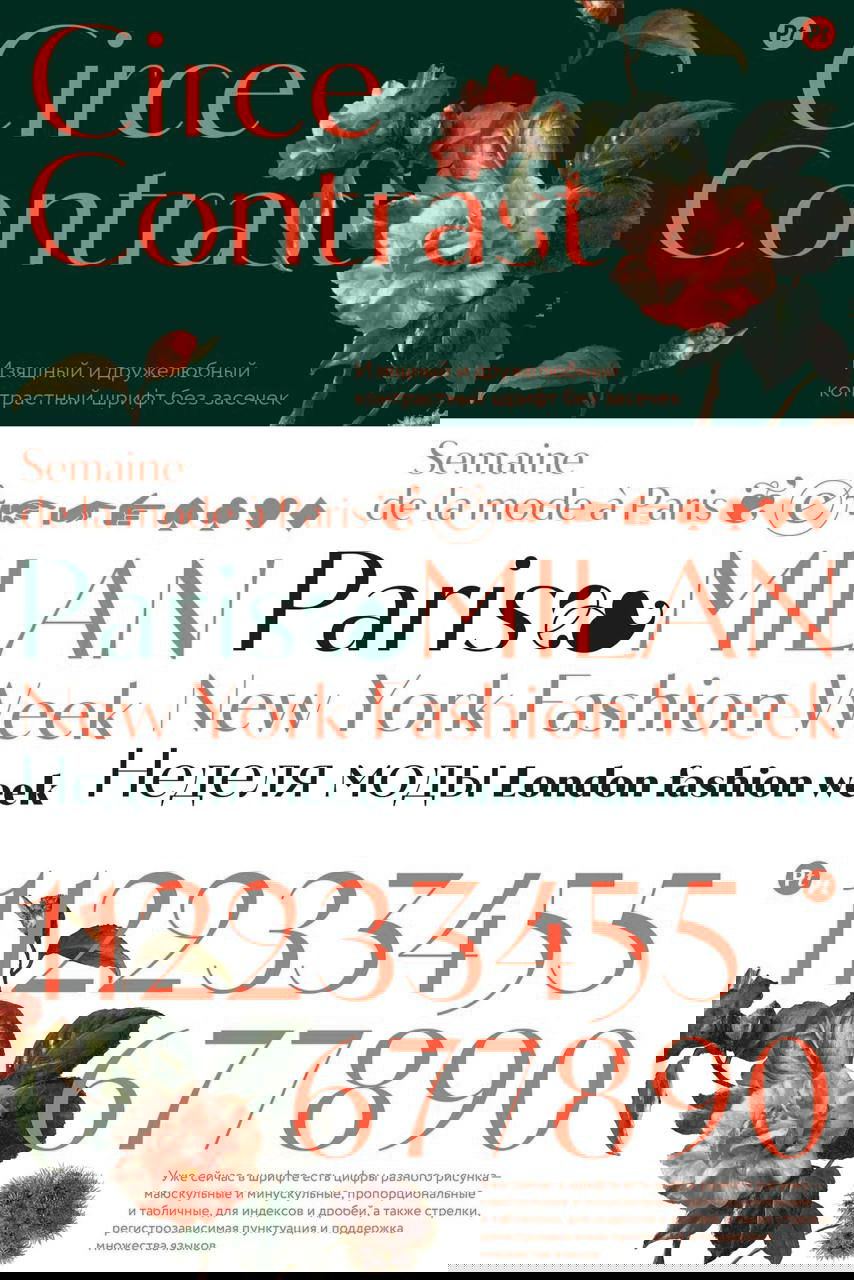
Изящный контрастный шрифт без засечек в лаборатории Paratype.
На момент публикации доступны начертания Regular, Black и вариативная версия с широким диапазоном насыщенности. Позже будут добавлены 27 статичных начертаний и курсивы.
Касса знаков включает цифры разного рисунка, стрелки, регистрозависимую пунктуацию и другие знаки. Поддерживает 115 языков.